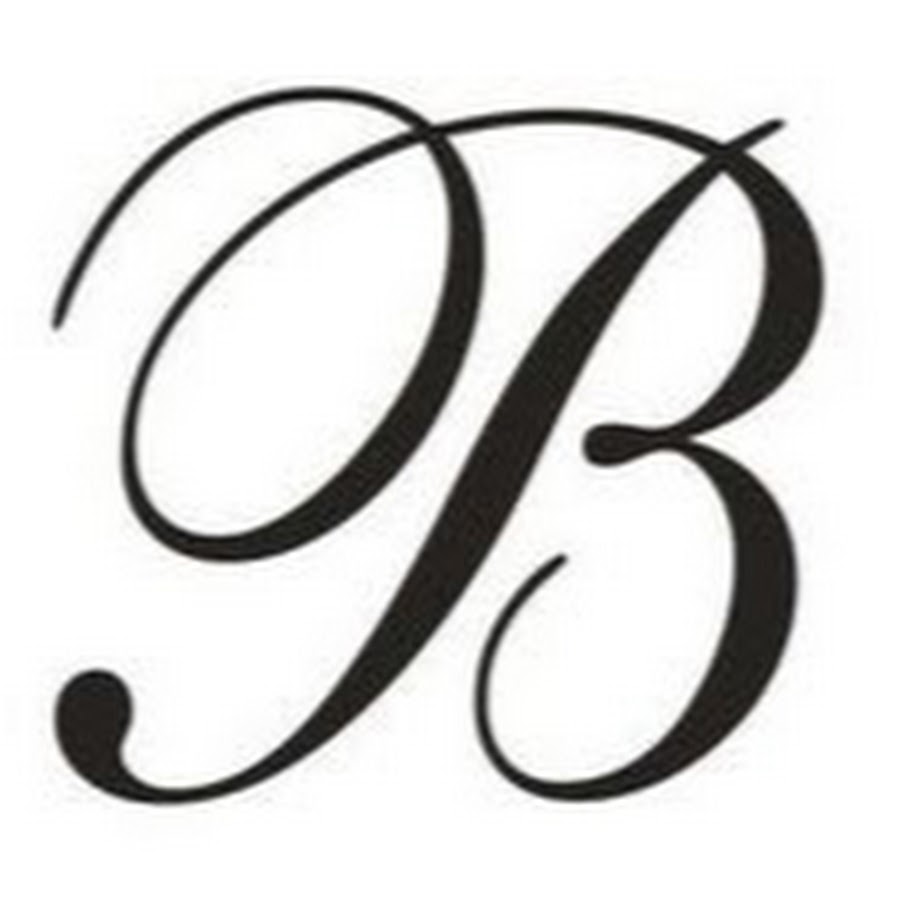
Красивые татуировки для девушек
В отличии от мужских, татуировки для девушек должны быть более изящными и утонченными. Они должны подчеркнуть женственность и красоту. Поэтому к выбору места и рисунка для татуировки девушкам нужно отнестись серьезно и тщательно взвесить все за и против. Тем более, что это на всю жизнь, так как безшрамовых методов сведения татуировок ещё не придумано. Представляем Вашему вниманию подборку красивых татуировок для девушек, с нежными и романтичными рисунками.
В последнее время среди девушек очень распространены тату на запястье. Чаще всего это фразы, цитаты и инициалы. Здесь Важно грамотно подобрать шрифт в зависимости от слова. Должен этот шрифт быть хорошо читаемый или трудно воспринимаемый, зависит отваших вкусов, главное, что бы он красиво подчеркнул девичью ручку. Для девушек предпочтительнее шрифты с вензелями.
Красивые татуировки для девушек на спине в виде надписи, тоже уже не редкость.
Тату в виде надписи красивым шрифтом с тенью во всю спину. На такое тату решится не каждая девушка. Надписи на спине смотрятся очень притягательно и сексуально.
Подобрать шрифт для татуировок — tutatu
Татуировки в виде надписей приобретают все большую популярность.
Большую роль играет правильный выбор шрифта, ведь их существует очень много. Нужно учитывать стиль написания, месторасположение рисунков, размер слов. Заглавная буква должна быть выделена наклоном, цветом или стилем нанесения.
Красивый шрифт на ноге
Различные вариации шрифтов позволят сделать татуировку в виде надписи красивой и оригинальной
Особенности татуировки шрифты
Татуировки в виде надписей смотрятся очень оригинально и красиво. Их очень любят наносить на свое дело голливудские звезды. В некоторых случаях надпись способна передать смысл татуировки даже лучше чем рисунок. Для этого очень важно подобрать правильный шрифт. Для женских надписей подойдут шрифты с глубокими изгибами, тонкими линиями и дополнительным декором. Для мужских надписей нужно обратить внимание на печатные буквы, применение жирного начертания, заостренные окончания. Татуировки шрифты, значение которых больше зависит от смысла самой надписи, одинаково распространены, как среди женщин, так и среди мужчин.
Выбираем язык и дизайн заглавной буквы
Как правило, шрифт зависит от языка. Однако наибольшей популярностью пользуется английский язык, поскольку он считается мировым. Для татуировки надписи, как правило, выбирают шрифты с вензелями и каллиграфические шрифты. Перед нанесением на свое тело надписи нужно определиться: будет ли это слово или целая фраза. Если вы хотите сделать надпись, которая начинается с заглавной буквы, то нужно обсудить с дизайнером ее особенности, поскольку не каждая заглавная буква будет хорошо смотреться. Возможно, дизайнер предложит вам выделить ее отдельным цветом или украсить дополнительными элементами. Татуировки шрифты, фото которых вы найдете не только на просторах интернета, а и в тату-салонах, позволят вам подчеркнуть свою индивидуальность.
Шрифт для татуировки в виде надписи может быть самым разным. Если вы сомневаетесь в выбранном стиле, лучше посоветуйтесь с дизайнером.
Четкая надпись сбоку тела у девушки
Правильно подобранный шрифт — это основа красивой татуировки в виде надписи
Любая надпись на теле должна быть читаемой, иначе она не сможет передать тот смысл, который вы хотели в нее вложить.
Виды шрифтов для нанесения татуировок в виде надписей
Татуировки шрифты, эскизы которых есть в каталогах салонов для нанесения татуировок, бывают нескольких видов. В современных тату-салонах отдают предпочтение следующим видам шрифтов:
- каллиграфическим;
- готическим;
- граффити;
- западным
Надпись на запястье, красивый шрифт
Есть и другие виды, но именно эти пользуются наибольшей популярностью. Стоит рассмотреть их особенности более подробно.